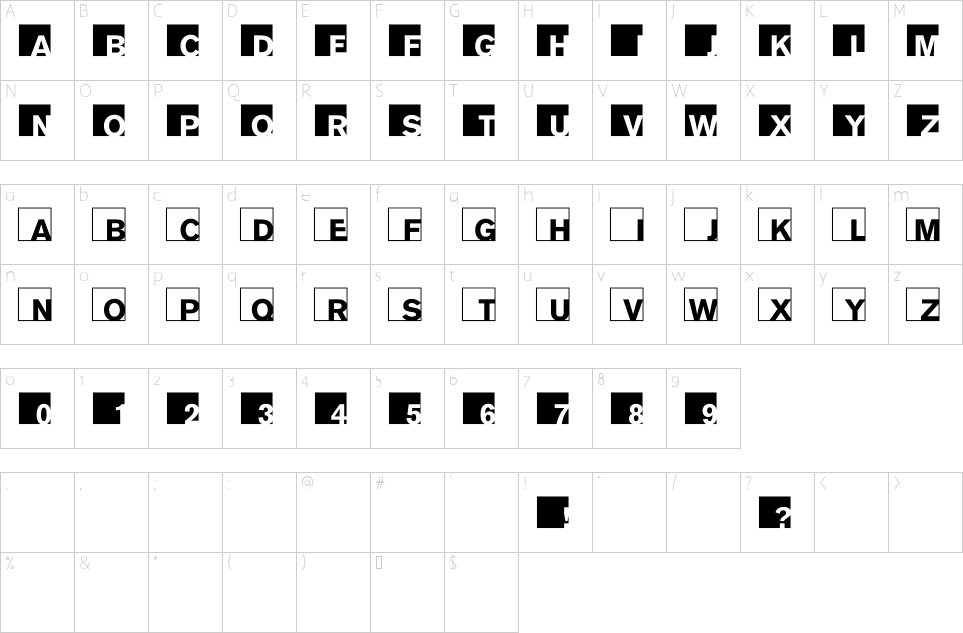
A fonte ‘ABC Logos XYZ’ é uma opção incrivelmente versátil para designers gráficos. Desenhada pelo designer Manfred Klein, esta fonte é uma seleção elegante e limpa que pode se adaptar a diversos tipos de projetos, desde identidades corporativas até materiais de marketing. Ela foi projetada para oferecer uma paleta de opções para diferentes tamanhos e tipos de texto, tornando-a perfeita para designers que buscam uma fonte moderna e de alto padrão para suas criações. Com a opção para download para ambos os sistemas operacionais Windows e Mac, ‘ABC Logos XYZ’ é um recurso indispensável para designers buscando opções gratuitas e de alta qualidade para suas necessidades. Com o download de mais de 13.300 vezes, é claro que designers do mundo inteiro apreciam e usam a capacidade única e elegante desta fonte.